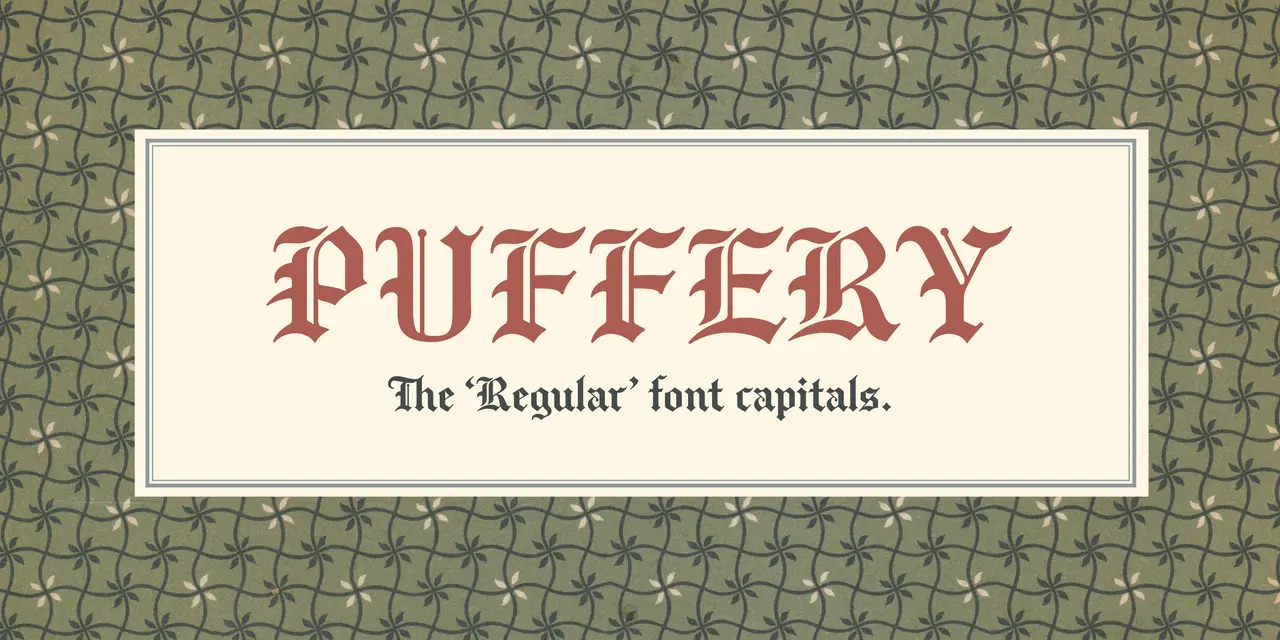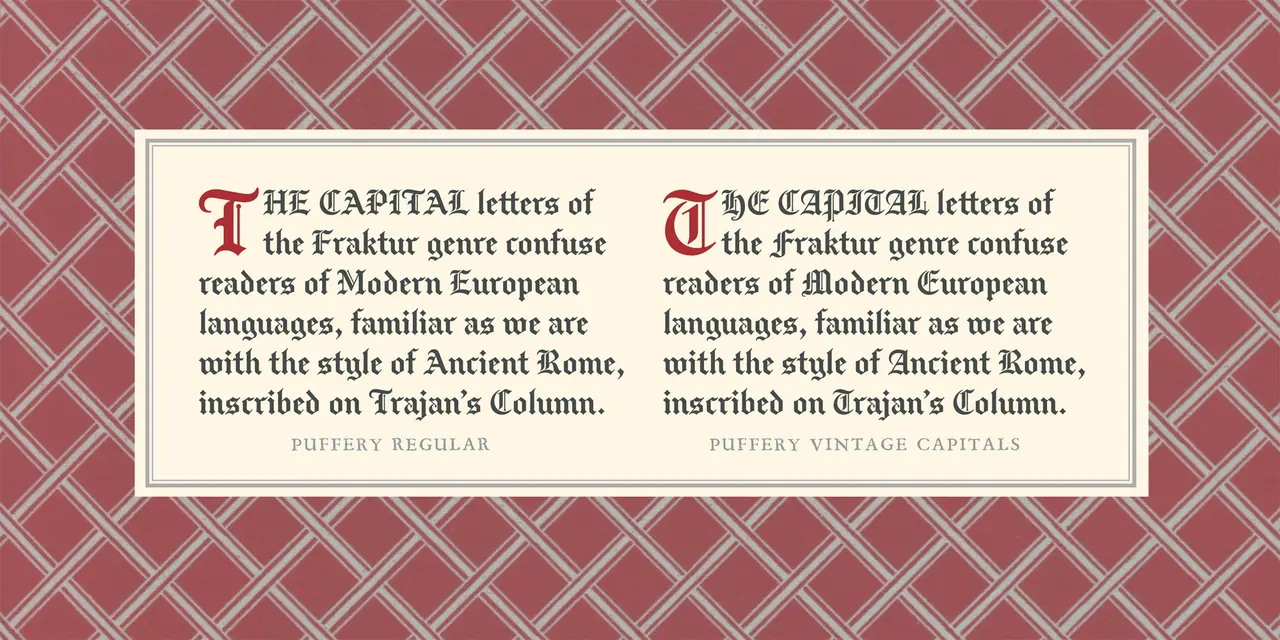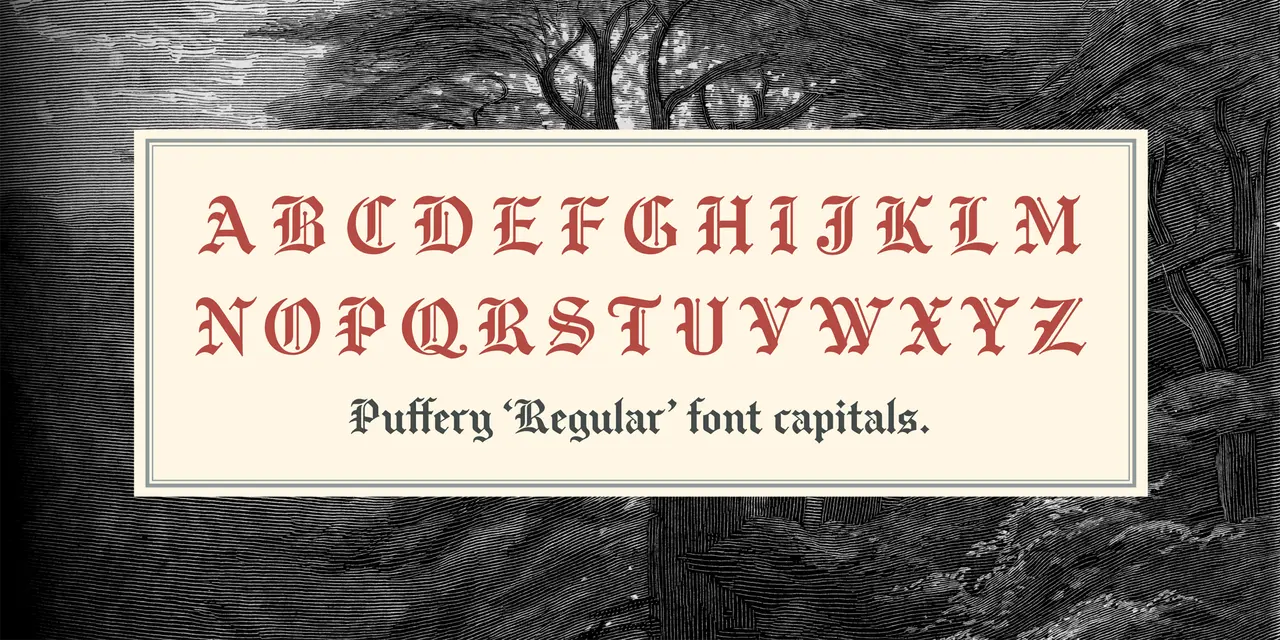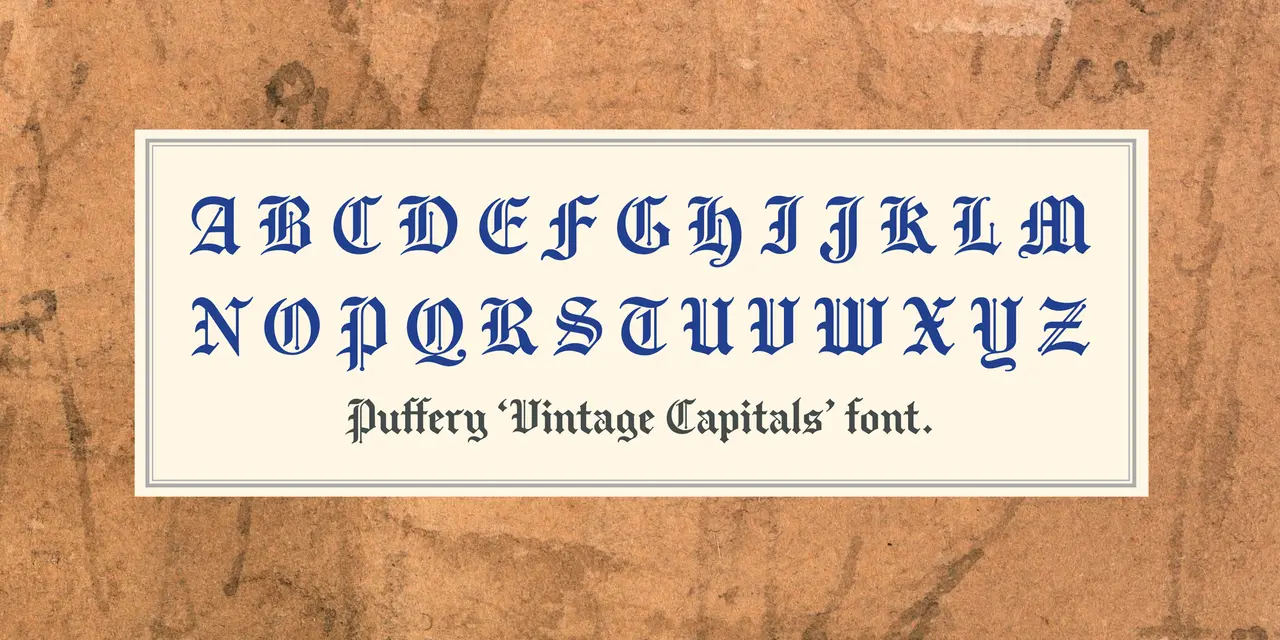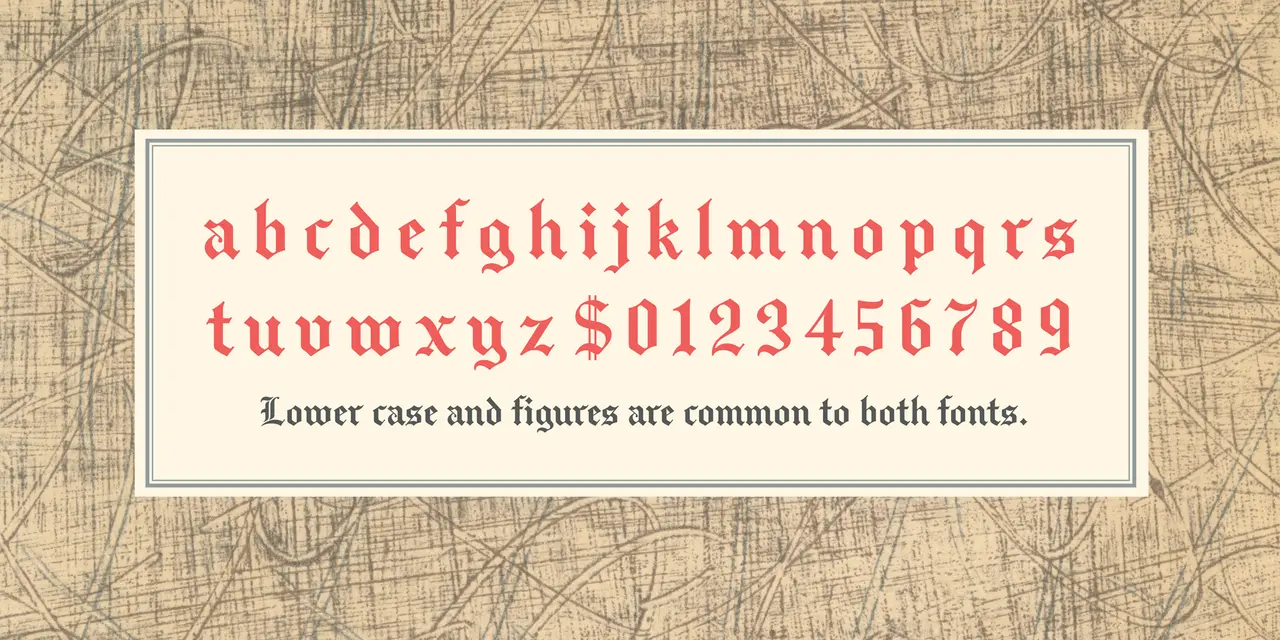
• Gebrochene Schrift
Die Puffery von Nick Shinn ist eine gebrochene Schrift im Stil einer »Old English«. Neben den entsprechenden, traditionellen Buchstabenformen enthält die Schrift jedoch als Standardbuchstabensatz Hybridformen, die sich trotz der enthaltenen Brechung an die Buchstabenskelette der Antiqua anlehnen. Entsprechend ist dann auch eine moderne und internationale Anwendung möglich, die Versalsatz laut Schriftgestalter ausdrücklich einschließt.